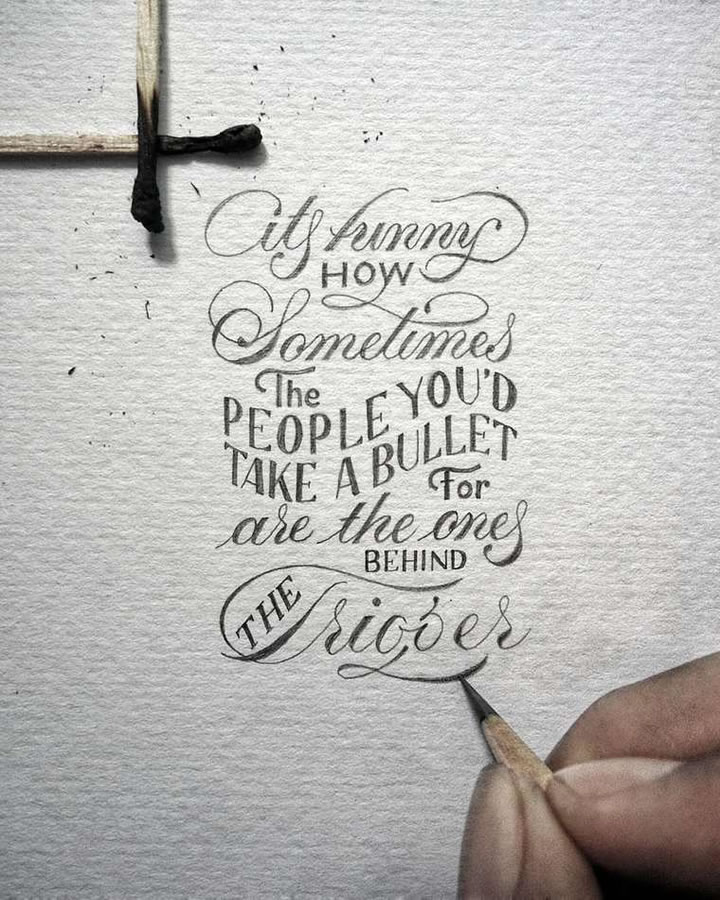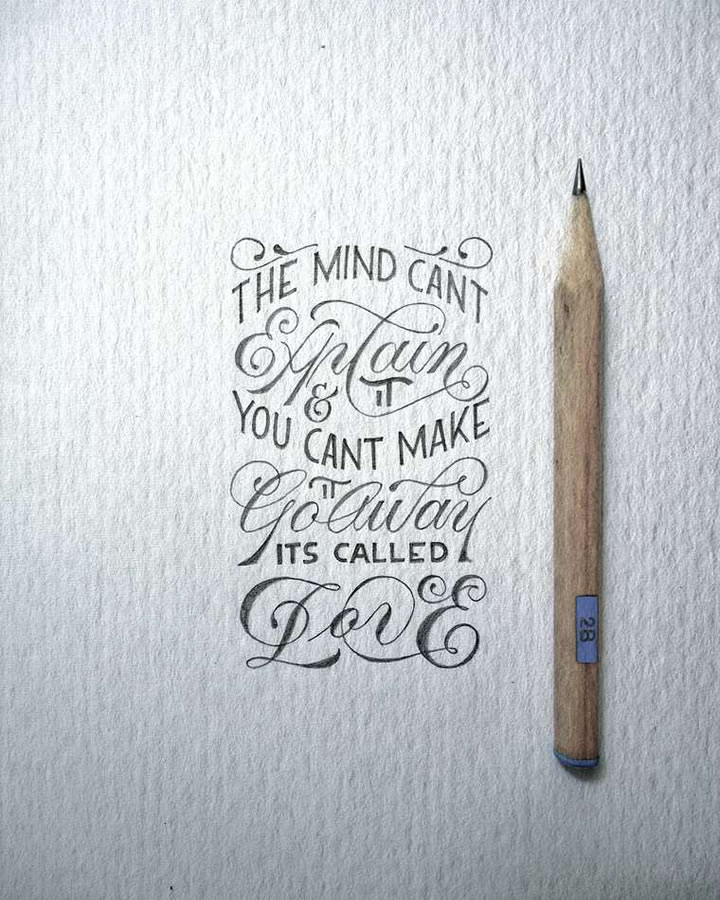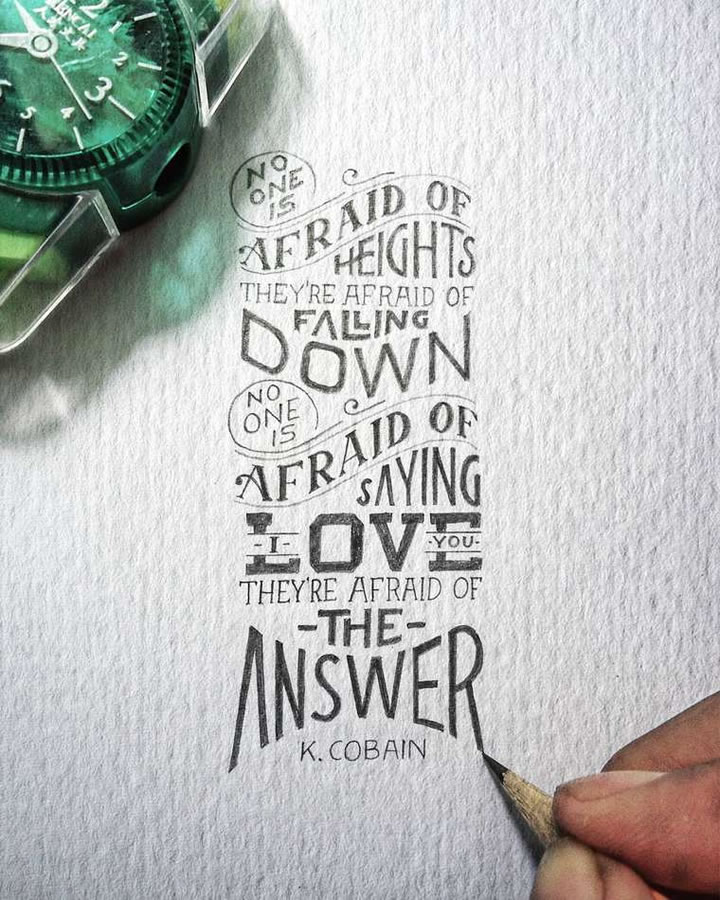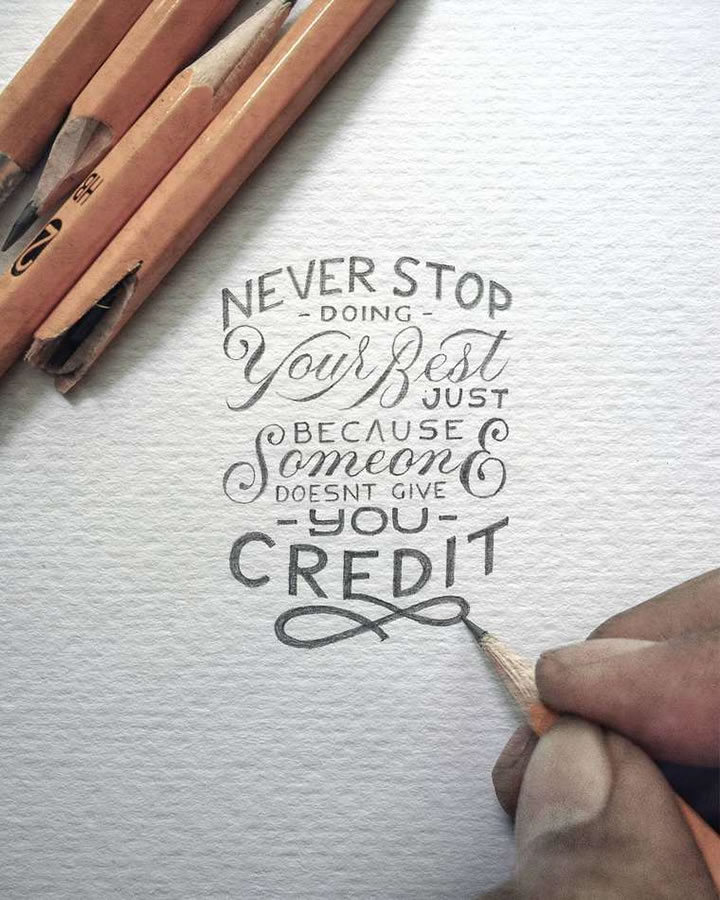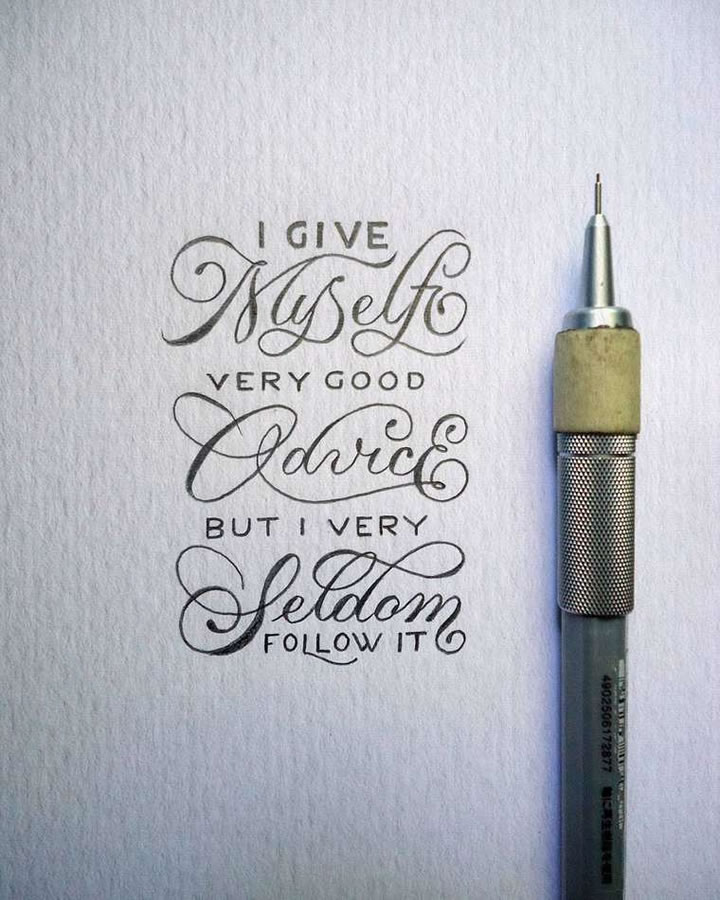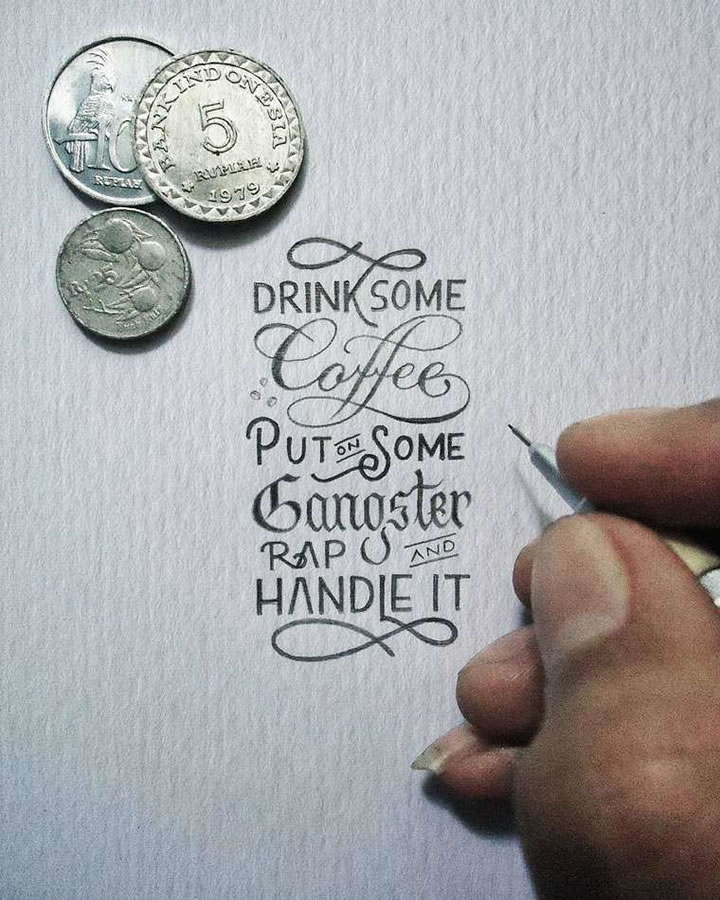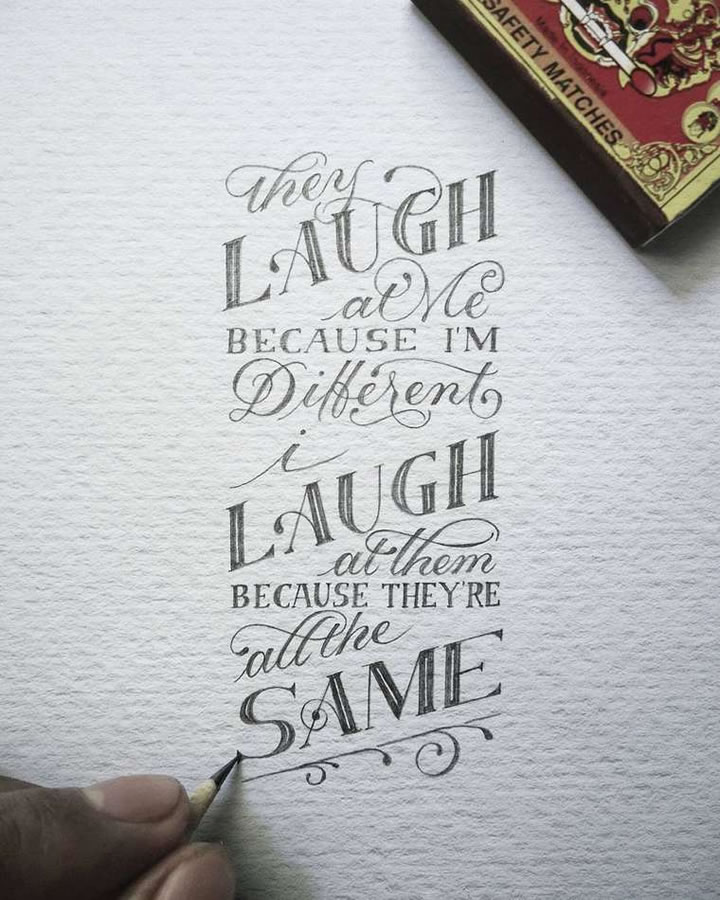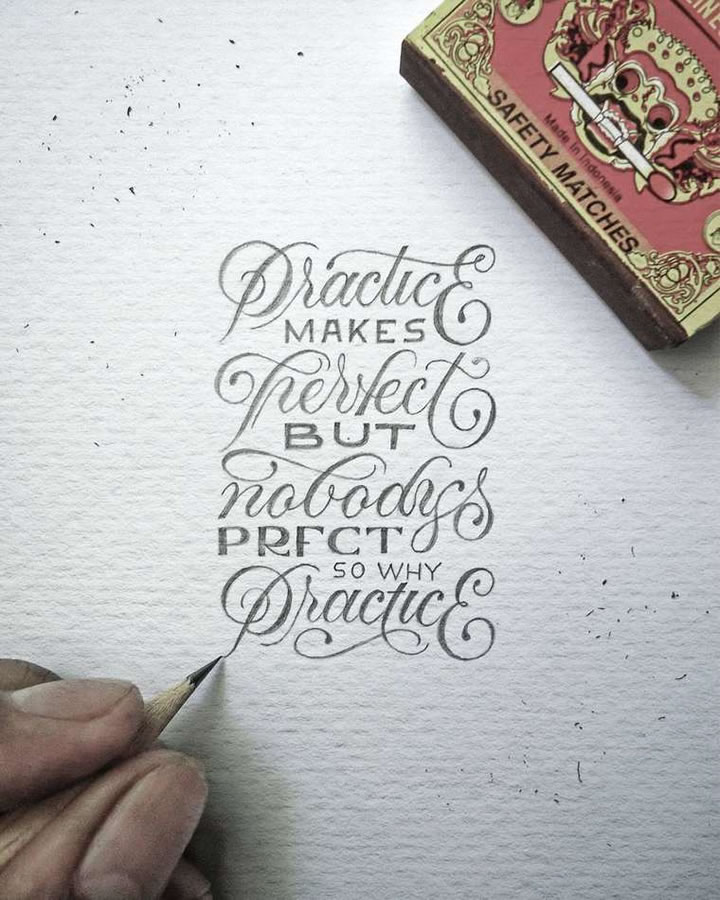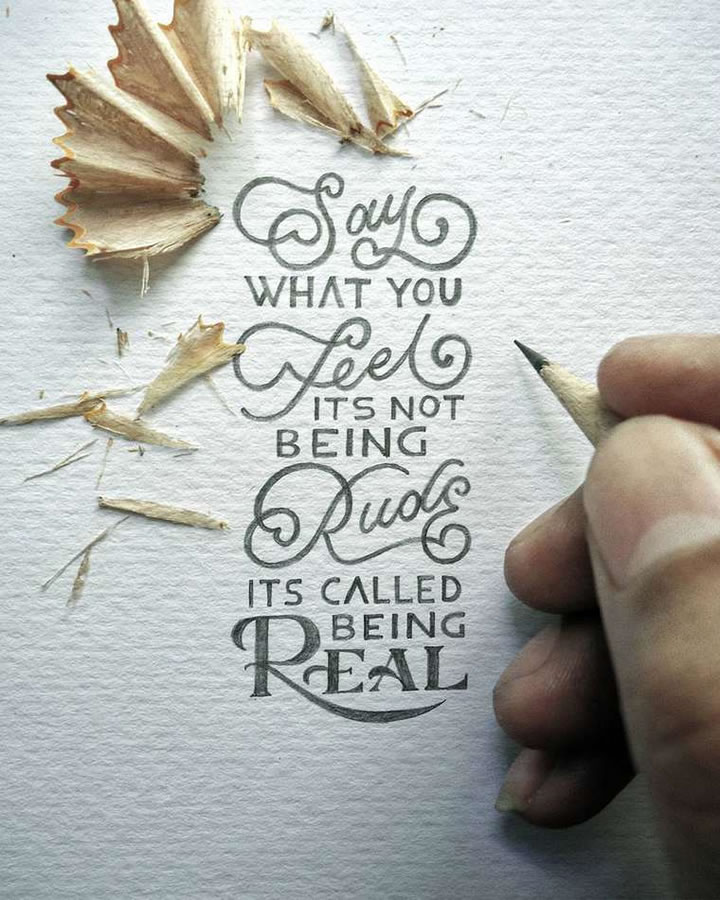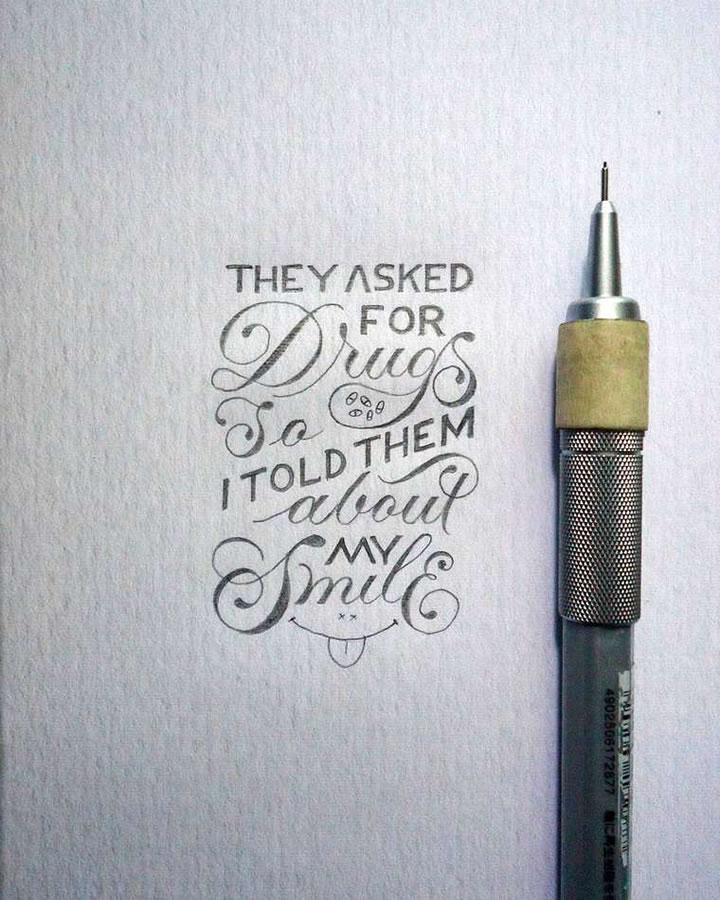
Réaliser de si minuscules jeux de typo doit prendre un temps fou, avoir une patience extraordinaire et une précision d’artiste. Dexa Muamar a réalisé et partage avec tous sur son compte instagram, des travaux pour le plus grand plaisir des yeux.
Les créations typographiques miniatures de Dexa Muamar